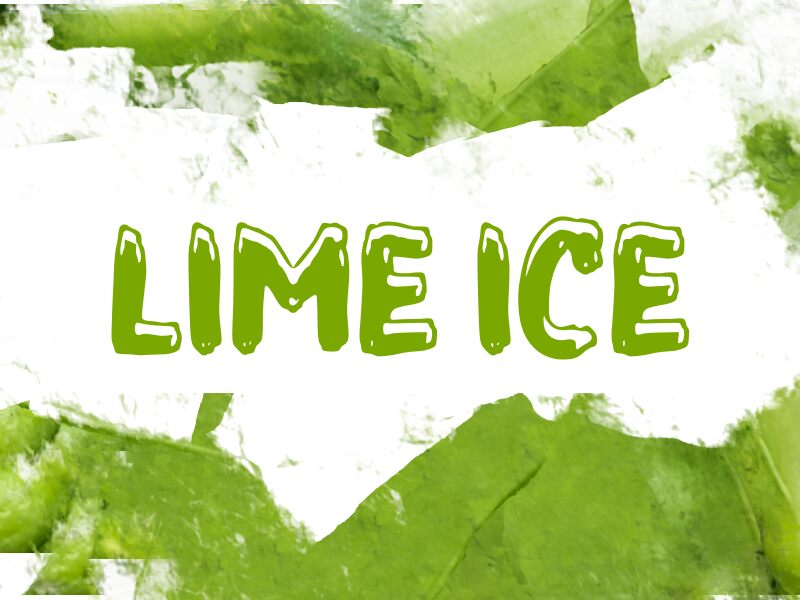
Lime Ice de Wep est une police display gratuite au style fondu, dessinée à la main, à la croisée entre la glace qui coule et le slime givré. Les majuscules sont épaisses, irrégulières et légèrement affaissées, avec des bords arrondis et des petites encoches qui donnent aux lettres un aspect humide, froid et volontairement imparfait.
Elle est idéale pour des titres d'affiches, des génériques de films d'horreur comiques, des flyers de soirée, des packagings ou des titres accrocheurs où une police gratuite suffit à créer toute l'ambiance. Utilisez-la pour vos mots courts, noms ou monogrammes si vous voulez un effet collant et givré : les lettres insufflent d'elles-mêmes ce mouvement doux et dégoulinant.